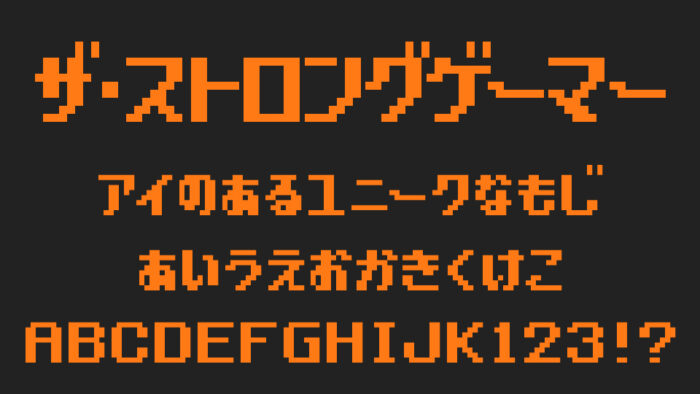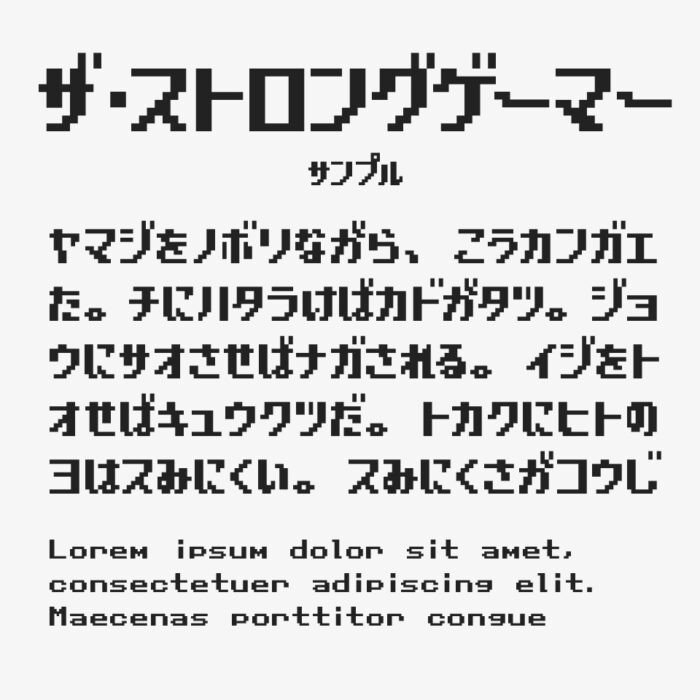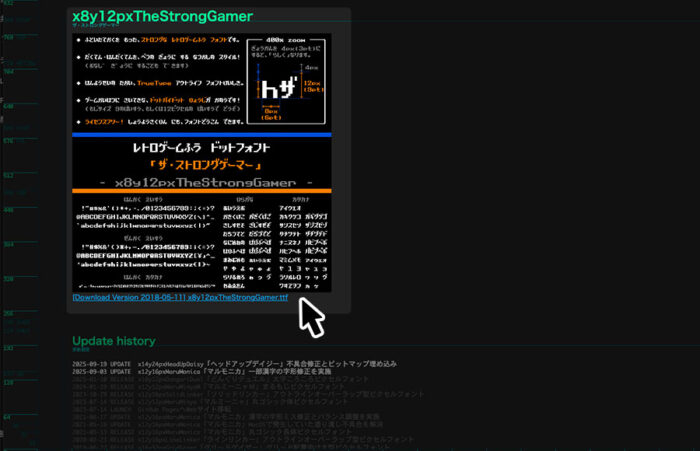
ザ・ストロングゲーマー
ザ・ストロングゲーマーフォントは、太めでカクカクしたドット調でレトロゲームの世界観にぴったりなピクセルフォントです。
一般的なピクセルフォントより太めに作られた文字で、80〜90年代のピクセルアートに通じる雰囲気が魅力です。太くはっきりとした線が画面上でも視認性が高く、重厚感のあるピクセル文字となっています。